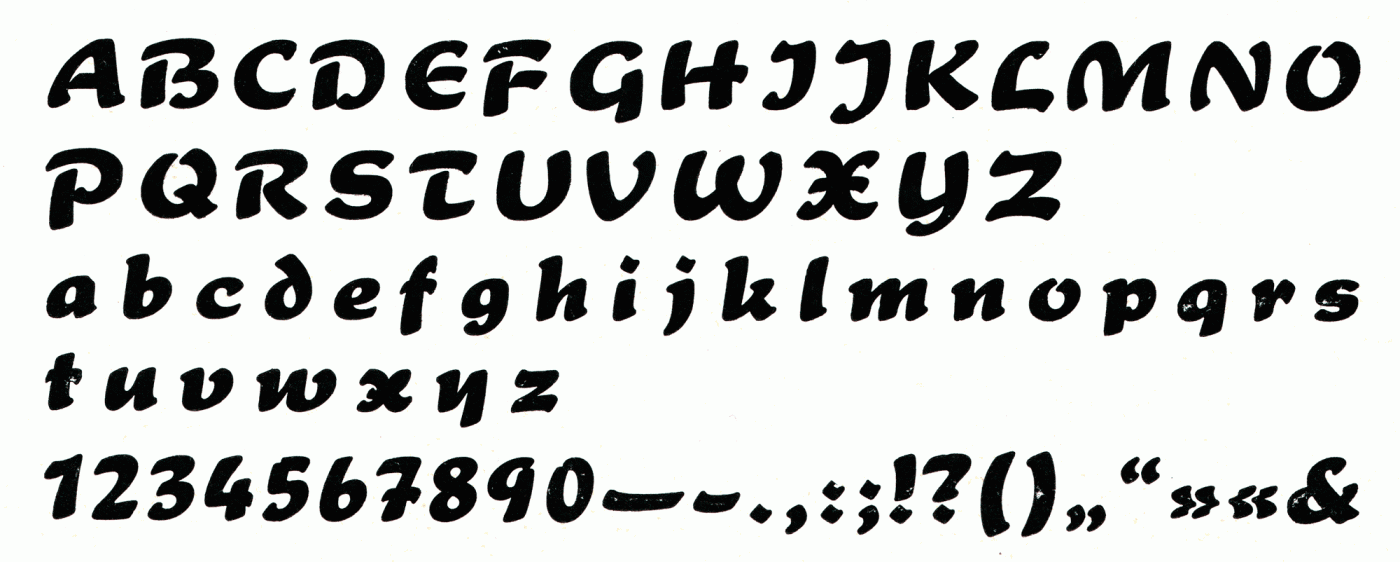
Font-Wiki: Gladiator
Die Gladiator von Hans Möhring erschien 1930 bei der Schriftguss KG in Dresden. Der Anbieter pries die Gladiator als eine Schrift an, »die mit eigenartig kraftvollem Ausdruck flüssigste Lesbarkeit verbindet. Gladiator ist aufs vielseitigste anwendbar und immer von äußerster Werbewirkung!«